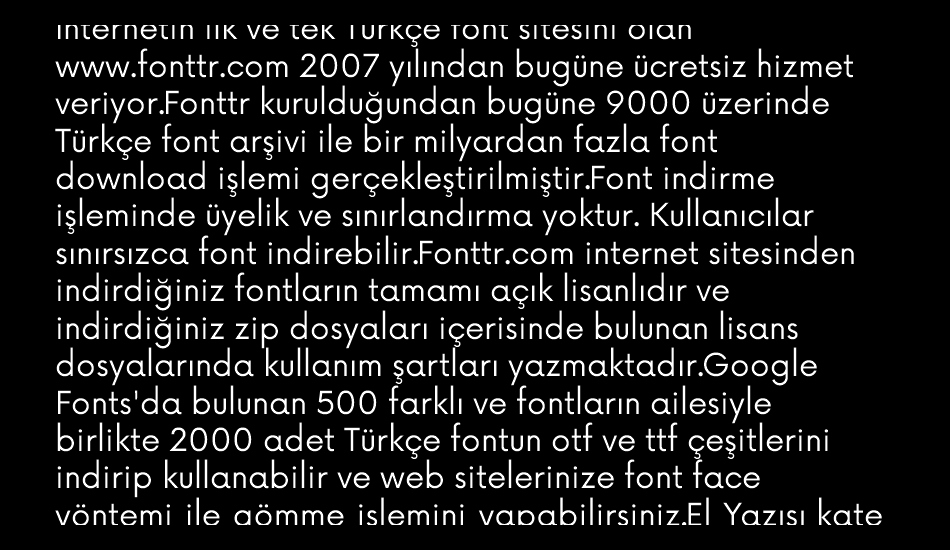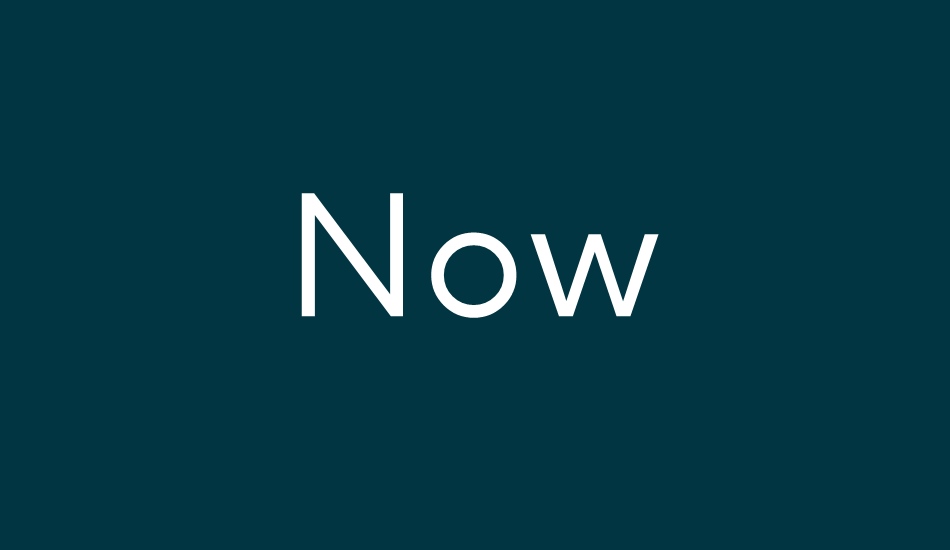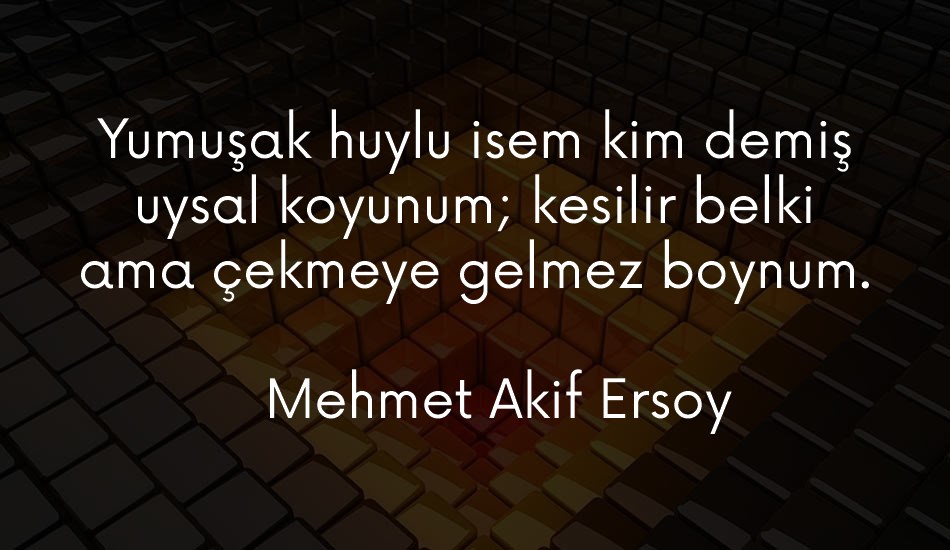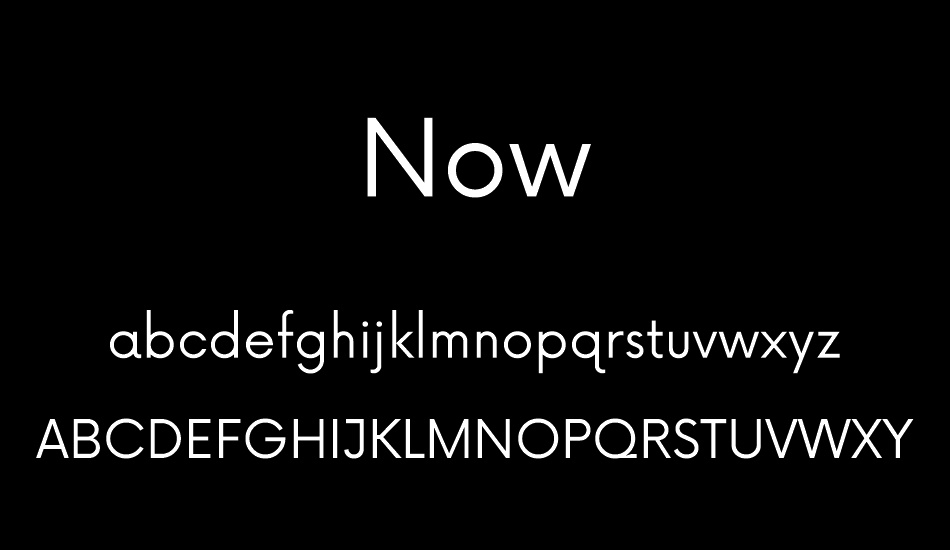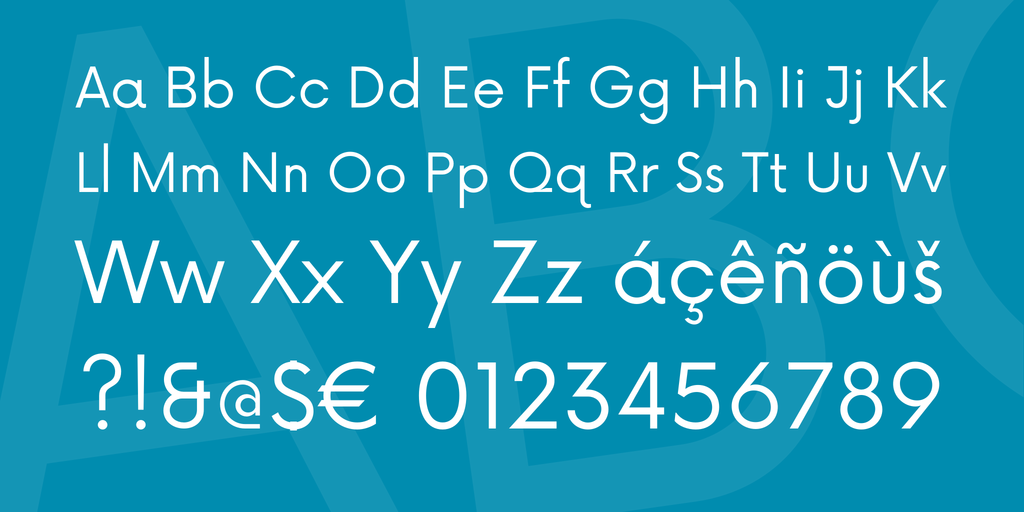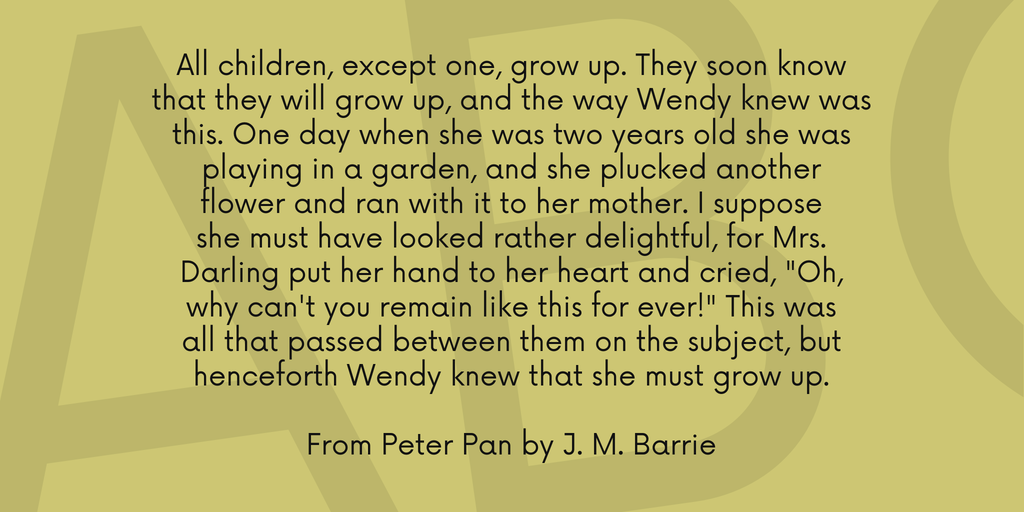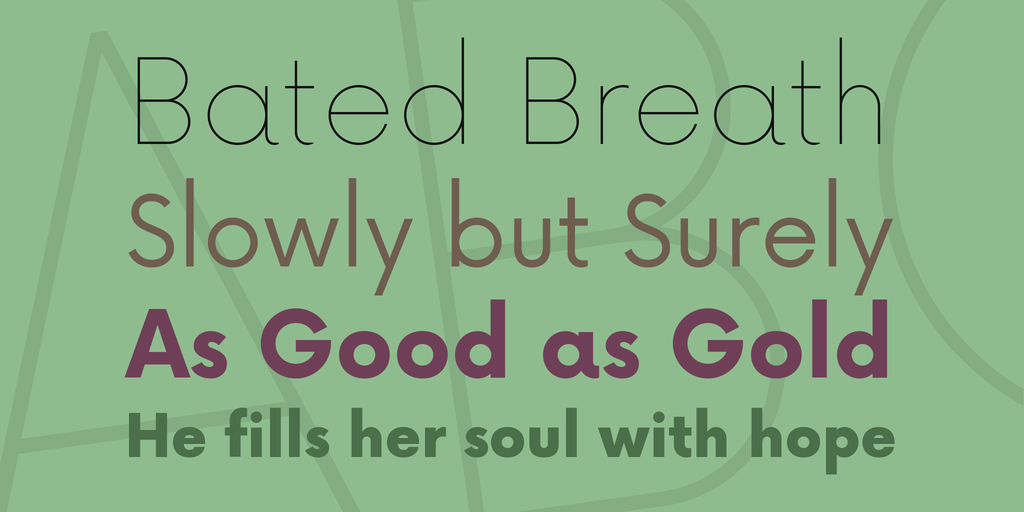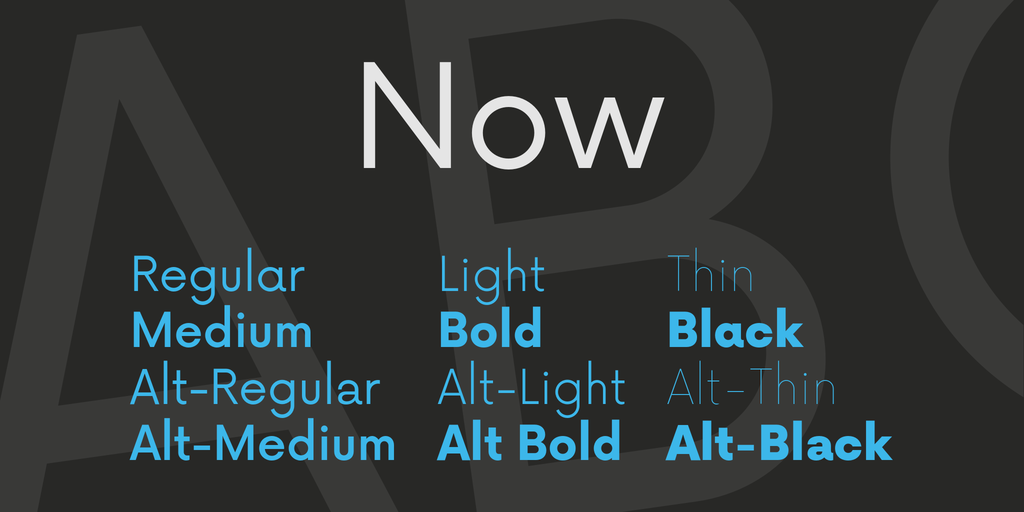
Now Font Ailesi font
Now Alt Tipi Alfredo Marco Pradil'in basit bir geometrik yazı formudur. Şimdi Yazı biçimi açık kaynaktır. Now Alt, Yazı biçiminin alternatif bir versiyonudur. Tek fark, küçük "a" dır.